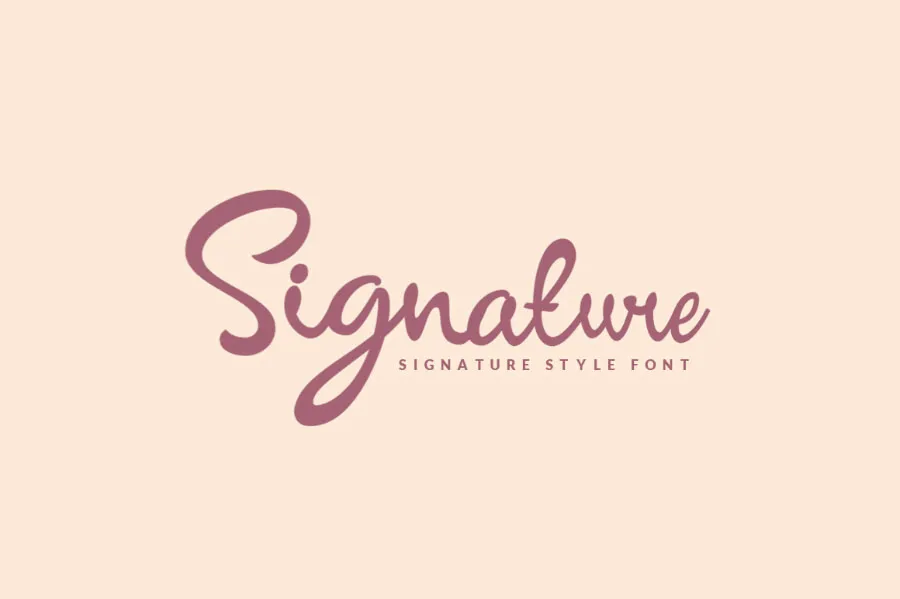
Signature Script Font – Download Grátis
Descubra a beleza única da nova Signature Script Font. Ela traz uma autêntica escrita à mão para seus projetos, proporcionando tanto estilo quanto criatividade. Desenvolvida pelo Designer ShowUp! Typefoundry, essa fonte tem um design inspirado nos nomes de assinatura, com letras estilizadas e impressionantes que se destacam por sua riqueza e originalidade. Perfumada para uma variedade de aplicativos, a Signature Script está ideal para logos, etiquetas de nome, citações escritas à mão, embalagens de produtos, materiais promocionais, mídia social e cartões de cumprimentos. Seus caracteres completos em minúsculas e maiúsculas permitem uma ampla variedade de uso, enquanto sua gama estendida de pontuação e números fazem da fonte um recurso útil para qualquer projeto. Obrigado a Hamilton pelo design cuidadoso desta fonte, que oferece aos designers o poder de criar escritas únicas, elegantes e criativas. Com esta fonte em seu arsenal de recursos gráficos, seus projetos podem ganhar uma personalidade ainda mais especial.